如果要给中国文化抽简出一个最终的极致符号,答案一定是汉字。它并不是人类文明中诞生最早的文字系统,却是生命力最长最旺盛的。从殷墟甲骨上那些斑驳不清的笔画开始,公元前 1300 年至今,朝代更迭,疆土分合,这片土地上无数次的易帜,文字却如最顽强的拥有慧根的藤蔓,在六书的形制上延续演化着文明的森林。汉字正在当代承受着悄无声息的冲击,这种从书写到输入的变化会带来怎样的结果?
01
电子时代,书写的重量
SHANG WEI
尚 巍
笔染时光工作室主理人、独立设计师、汉仪字库及方正字库签约设计师、站酷千万人气设计师、《了不起的匠人2019》专访艺术家、全球首位为SAMSUNG三星品牌发声的艺术家、戴尔中国2020品牌合作推广人,著有《字不语》。代表字体库作品:汉仪尚巍手书、汉仪尚巍清茶体、汉仪尚巍少年体等。
尚巍与他的书法作品
4年前,25岁的尚巍从著名设计公司洛可可辞职,身上只有600块的他,在北京的出租房里一个人待了21天,用毛笔写完了9,169个汉字,完成了自己第一套手书字体“汉仪尚巍手书”,短短三个月之内它成了全国最畅销的字体,从平面海报到电视节目,尚巍都能看到自己的字。其实在孤注一掷发布这套字体前,尚巍预估过两种极端情况,要么短时间内获得大众口碑,要么被一部分推崇传统书法的人骂到风口浪尖上。结果这两种情况同时出现了。
尚巍从小学习传统书法,每天坚持习字
从5岁开始学习书法,到第一套字体推出,尚巍写了20年的字,几乎每天都要写。即便如此,从洛可可辞职的时候,尚巍并没有想去做什么字体设计师,更没考虑过手写体。当时他是满怀希望地准备去找下一份工资更高的工作。可是离开办公室前,挽留他的副总裁说了一句话,彻底刺到了尚巍的心里,“你离开这儿,在北京能养活自己吗?”
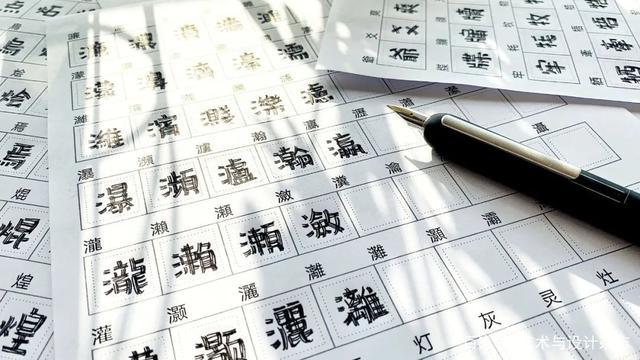
尚巍手书字库手稿“荒野体”
就因为这句话,在回家路上尚巍产生了一个念头,与其上班,不如试一试去做自己坚持了20年的事——写字。“如果赢,就赢了,不赢,我也是个‘破罐子’不怕摔一下。”
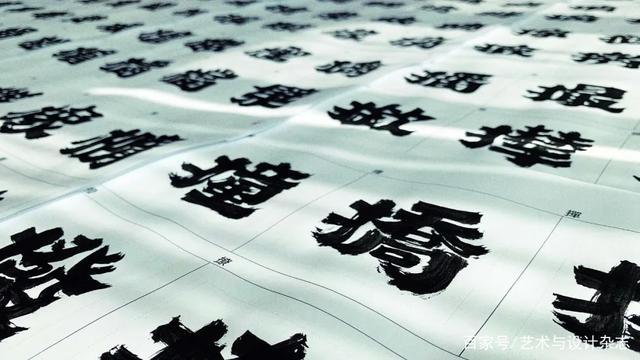
尚巍手书字库手稿“墨游体”
在进一步思考该怎么做,具体该怎么写的时候,尚巍反倒是回想起了平面设计过程中的一些经验。往往设计师想要一款比较有视觉冲击力的字体时,需要用各种素材拼字,耗时耗力,所以他想做一款一直没有过但设计师非常需要的字体。
我热爱它
只要能让我在北京生活
哪怕是生活得非常苦
我写的
每一个字一定是因为热爱
完成第一套字体尚巍手书后,拿到的钱虽然不多,但足够他在北京交几个月房租。到现在,尚巍已经完成了十几套手书字体,虽然内心充满了热爱,但每一次的创作周期都是一个痛苦的过程。从最初想赚房租,想在北京活下去的单纯奔头,慢慢地尚巍身上多了些行业责任感的包袱。尚巍觉得,这4年来自己靠的从来不是什么乍现的灵感,而是靠“憋出来”的,他常常把自己关在房间里,告诉自己不能停下来。
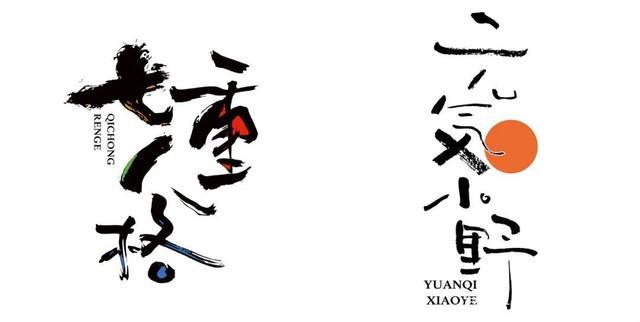
尚巍尝试不同风格的字体设计
尽管尚巍没想继续走传统书法的路,但只要拿毛笔写字,总有人上纲上线绕进“传统书法领域”。尚巍手书火了,尚巍也成了传统书法一派攻击的活靶子。对传统书法依旧充满敬畏和热爱的他,一腔热血也曾因这些批评覆灭过。“所以后来再有人问我,为什么做手写体,我就说我喜欢赚钱,这样别人骂我的时候,我心里就舒坦多了。”尚巍现在还是充满反骨的人,但他内心清楚地知道,“是因为热爱,想安静地做自己的事,放飞自我,懒得表达。”
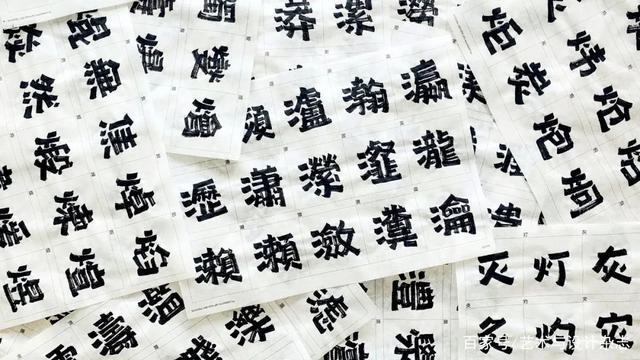
尚巍手书字库手稿“古书体”
书法,是中国文化土壤中孕育出的一种特有的视觉艺术形式,在世界艺术中独树一帜,千年以来拥有巨大的影响力。现当代艺术兴起后,这种古老的艺术也在寻求新的可能,现代书法逐渐成型,不少人被质疑过,批评过,却没有办法改变,艺术和创作本应不受拘泥的本质。尚巍说,自己写得不是传统书法,只是手写体。也正是因为手写体,他的字才如此受欢迎,因为没人能否认在这个输入的时代,书写的温度显的特别珍贵和动人。汉字的魅力难道不正在于此吗?点撇横竖之间能藏天地,能见人性。手写,是我们对汉字最初的敬仰和最后的留恋,也是继续它生命的创造之路。
02
把文字还给自然
GUAN LEXIAO
官 乐 霄
LEXIAO DESIGN平面设计公司创始人。毕业于英国皇家艺术学院的视觉艺术家,于2015年在伦敦设立Lexiao Design。
官乐霄说,背井离乡在不同文化环境下成长的人都会有一个时刻,一个moment——“别人问了你一个问题,然后让你产生了身份认同的危机。你回想,我到底是谁。”
刚到伦敦没多久,还在读本科的官乐霄认识一个很喜欢哲学的意大利同学,他问了官乐霄有关老子和孔子哲学观点差异的问题。这就是官乐霄身份危机的那个moment。“我突然发现,自己只了解一点皮毛,其余的什么都不知道,一个外国人竟然知道得比我多,我是不是特别丢人。”从这一刻的“打击”开始,官乐霄逐渐真正走进了中国传统文化的世界。
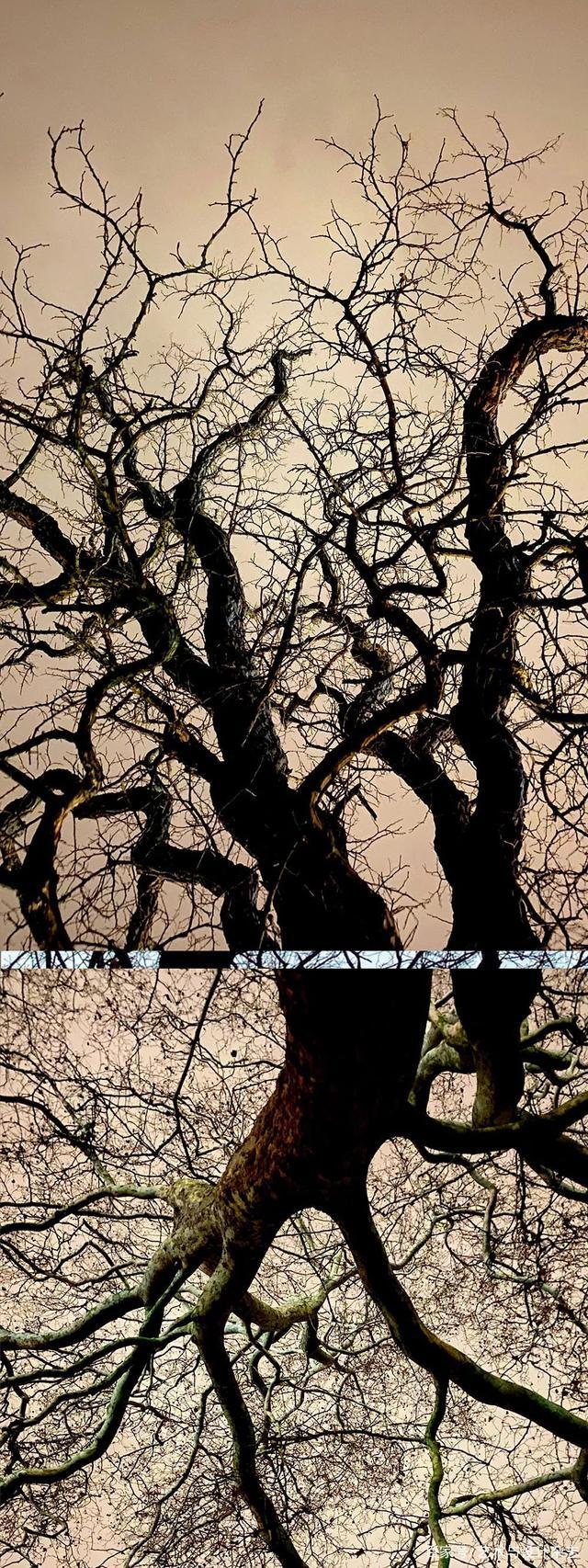
《象形文字》系列
今年,他以自己从甲骨文和宋代书画那里获得的灵感为基础,创作成了新作品《此彼之桥》。“作为信息时代的后生,我的作品在尝试重塑传统经典。”其中最让人印象深刻的《象形文字》系列以甲骨文的产生和形态为创作源头,将现实中拍摄的树木的照片根据甲骨文的结构进行有机的重组,并几乎以等比例呈现于尺幅近2米的纸张上,画面中所展示出的独特的生命里跃然纸上,似在展览空间中生长。“它们的生命力就在那里,在人类的想象力前充满了各种状态、情感、结构、起停、表达,还有方向。”官乐霄解释道,这既是他对作品的解读,也是他对于甲骨文形态的理解。
出土的甲骨文残片
甲骨文是官乐霄了解传统的文化的切入点。这种古老文字反而与他现在所学的平面设计更为相关。字体在平面设计领域是很重要的部分,一个好的设计师必须学会观察字体。中文字体本身包含的结构关系和表达功能,能同时满足市场需求的设计和研究需求的视觉传达。而汉字不论是结构还是节奏都可以追溯到七八千年前,能够把复杂各异的形态凝练起来,同时保留它的神态。
均为《象形文字》系列
从最初的灵感来源谈到这次作品的具体呈现形式,官乐霄希望我们能够感受到其中微妙而隐秘的关联性——不论是文字还是诗歌,存在于内部与外界之间——西方的文明是做“定义”,而我们的文明则擅长做“比喻”。
出土的甲骨文残片
的确,我们文字产生的源头便是模仿与比喻。在农耕社会下,我们祖先与自然保持了密切、亲近的关系,甲骨文中的很多字是直接描画了原物的形象,也就是象形字,这也是文字中最早出现的一部分。由此可见,中国的文字来源于自然。
我们祖先在创造它们的时候
一定是发现了
某些多于我们认知的东西
在我们的认知之下
还有更深层的内在连接
这是一种情感的共鸣,一种节奏的共鸣
我现在是把甲骨文还给自然,让它回归
因此,在官乐霄《象形文字》的作品中,他试图重新构建文字与自然之间的关联性,他试图在自然界生长的事物中间,去找寻隐藏的文字的“天然性”,以及它们之间结构上的本质相似。在他看来,甲骨文对其他事物的比喻和连接就像一支画笔,能让人产生更多的联想。
半个世纪的汉字匠心
ZHU ZHIWEI
朱 志 伟
字体设计师。曾任方正字库字体开发总监,现为汉仪字库艺术总监。主要代表作品有北魏楷书、铁筋隶书、方正博雅宋、方正雅宋等,同时也是中国人民解放军海军于2012年启用的舷号字体的设计者。
特写活字印刷铅字印刷版
1971年,16岁的朱志伟刚刚初中毕业,被分配到了北京外文印刷厂成为了一名刻字工人。在那里朱志伟第一次接触到了印刷字体,也不懂什么设计,只是给缺字的字模补字。但在他看来这不是个可以马虎应付的“简单的小活儿”,刻字是一份非常细致的工作,除了做到“随体”的要求(即刻出来的补字放入原来的文章中,需要跟原文其他字体保持一致。)之外,朱志伟渐渐开始琢磨汉字形体中的细节——笔画线条要利索,空档要干净,也要讲究传统书法中“计白当黑”的美感。
中国汉字与活字印刷术
20年宝贵的刻字工作,成为了朱志伟最宝贵的人生经历之一。“我比较特殊的经历在今天,在这个行业里很难再找到了。”在字体行业已经工作了50年的朱志伟感慨道。
1988年,因为印刷厂的合作项目,朱志伟被派到深圳科技工业园,协助朱邦复(“中文电脑之父”,是中文终端机、仓颉输入法、汉卡的发明人。)工作室开发中文字体。在这里,朱志伟第一次接触到了电脑及电脑字体。当时除了日常工作外,每天下班后,朱邦复便给大家“讲课”,讲汉字的分类、汉字的智慧,虽然只在这里工作了短短1年的时间,却对朱志伟的人生产生了转折性的影响,他意识到刻字已经不会有出路了,电脑造字才是未来中文字体设计的方向。
1991年,朱志伟离开了工作了20年的北京外文印刷厂,被王选招进北大方正。虽不用一刀刀刻字,但简单的把关和管理工作也与想象的不同,朱志伟想找到一条出路,便开始寻找隐藏在汉字中的基因密码。
中国汉字与活字印刷术字模
早期方正字库并不直接设计汉字字体,而只是从老字模厂购买原有的铅字字稿,再对照着字稿把汉字按照一定比例放大描在稿纸上,扫描进入电脑后重新进行调整,例如我们最熟悉的宋体、仿宋、黑体和楷体。这个过程比较机械,没多少创造性。没过几年,字模厂的字稿已经差不多用完了,对新字体的需求被提上了日程。
字体是与社会同步发展的
社会发展到什么程度
发展到什么水平
就会产生与社会相适应的字体
一直以来朱志伟收集、整理、研究了各国的报纸,特别是跟我们字体相似的日本,他发现相比字号大,字迹清晰整齐的日本报纸,我们的报纸在整体视觉和阅读效果上都很不如人意。中国报纸几十年如一日地统一使用着由上世纪60年代从日本进口的“秀英体”改良后的宋体字,也被称为“报宋”。铅字印刷时代,要给铅字留出“吃墨”的距离,字模笔画做得纤细,而数字时代的排版这个传统问题完全不存在了,字体也就必须得跟着变。
不同字体中提炼的笔画造型
更重要的是,朱志伟凭着对汉字字形的熟悉,慢慢总结出了当代造字的密码。他整理出了包含汉字基础部位30个笔画的25个字,从它们出发,便能拼出500个基本字,接着就是2800个常用字。